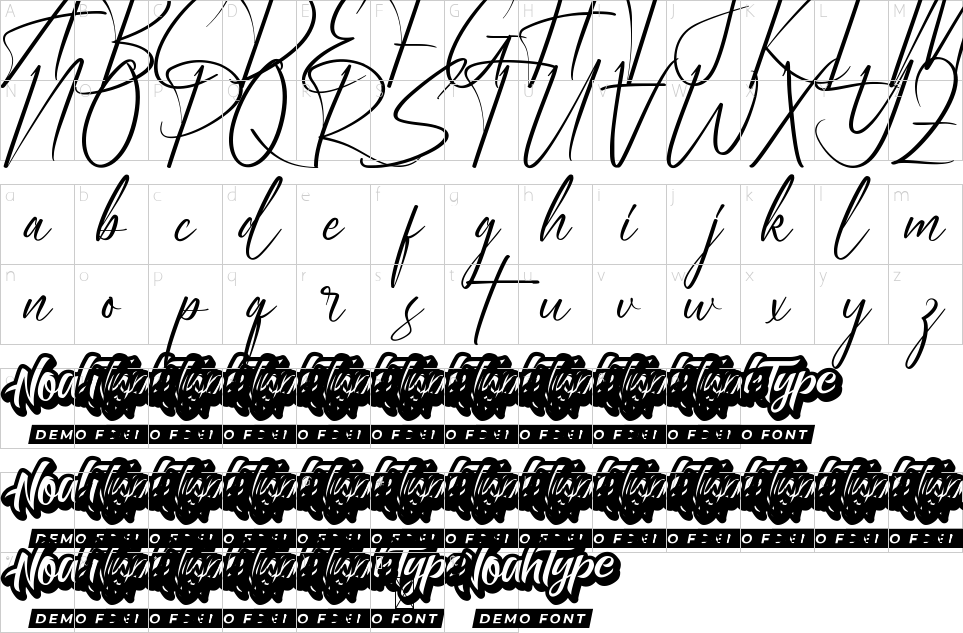
Manchester Park Font | 1001 Free Fonts – Download Grátis
Manchester Park é uma fonte urbana e moderna que se destaca em ambientes digitais do Brasil. Desenvolvida por não informado, essa fonte combina elementos de estilos de letras urbanos e futuristas, criando uma experiência visual única. Ela é ideal para criações digitais que precisam de uma sensação de contemporaneidade, como design gráfico, criação de logomarcas, ou até mesmo para personalizar sites e aplicativos. A fonte é versátil, adequando-se tanto para títulos quanto para textos de corpo, tornando-se uma opção ótima para estilos de design que valorizam a sofisticação e a modernidade. Com uma baixa frequência de download, Manchester Park é uma fonte que oferece uma dose de exclusividade para aqueles que procuram algo mais atraente e ousado para seus projetos digitais.